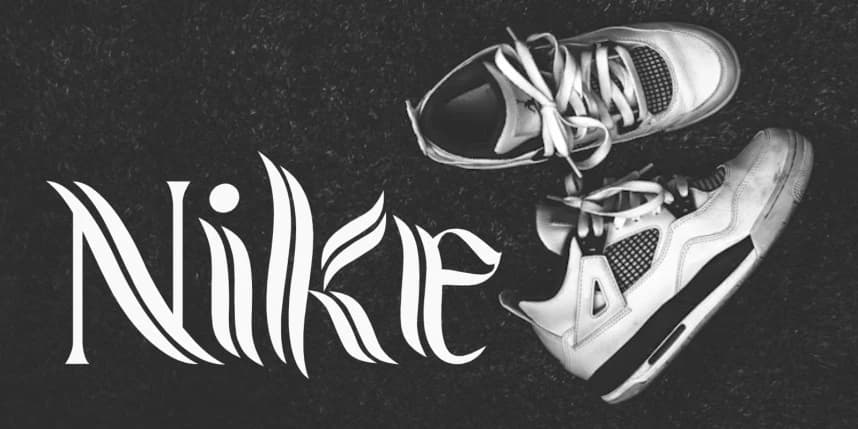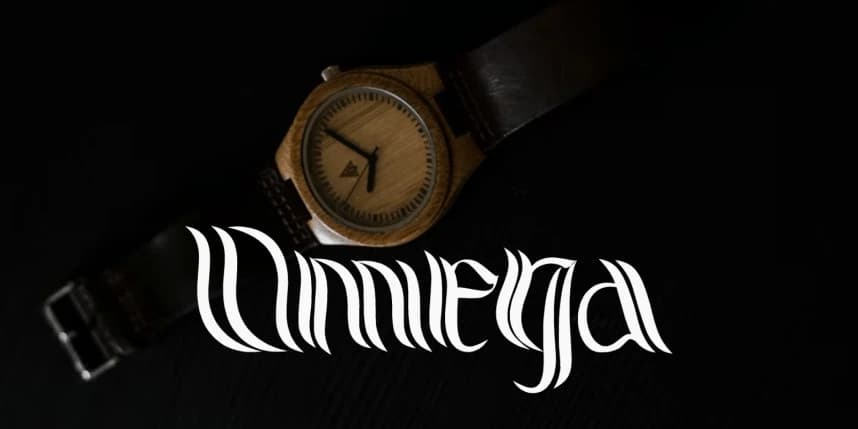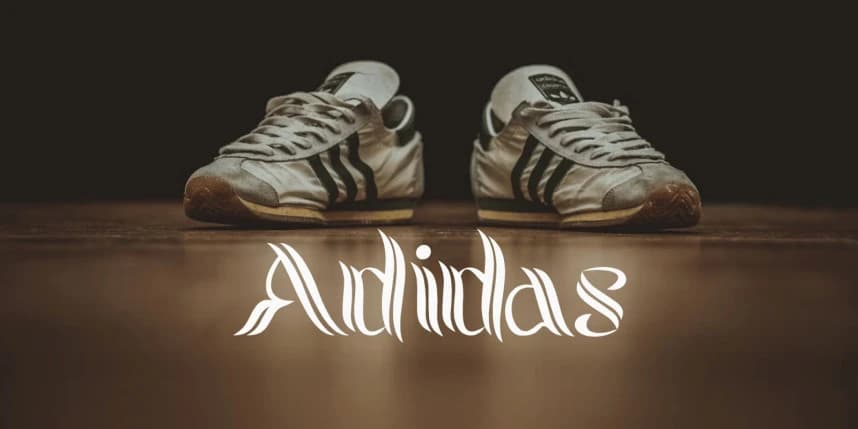
Mytik Yazı Tipi
Mytik Font, eski efsanelerden ve mistik enerjiden ilham alan cesur ve gizemli bir gösteri yazı tipidir. Keskin eğriler ve dramatik harf biçimleriyle Mytik, sihir, fantezi ve anlatılmamış hikayeler hissi uyandırır.
Mytik Font, eski efsanelerden ve mistik enerjiden ilham alan cesur ve gizemli bir gösterim yazı tipidir. Keskin kıvrımlara ve çarpıcı harf biçimlerine sahip olan Mytik, sihir, fantezi ve anlatılmamış hikayeler duygusunu uyandırır.